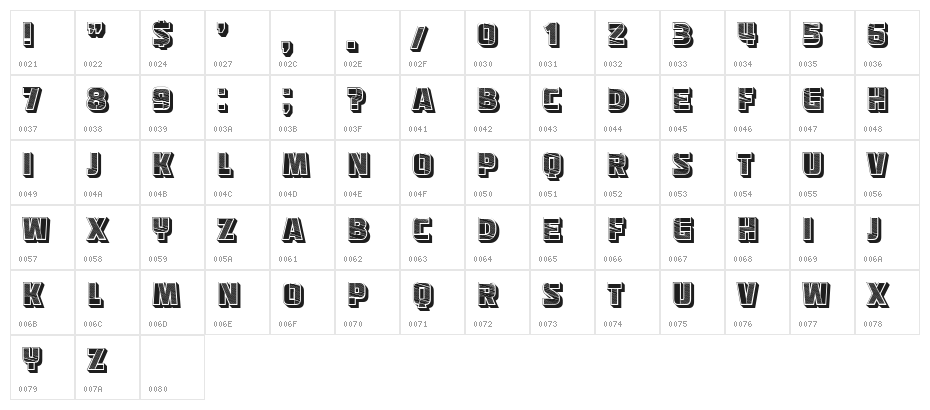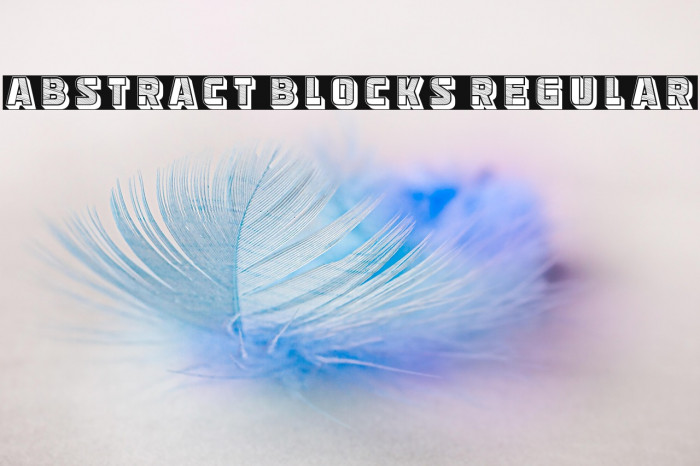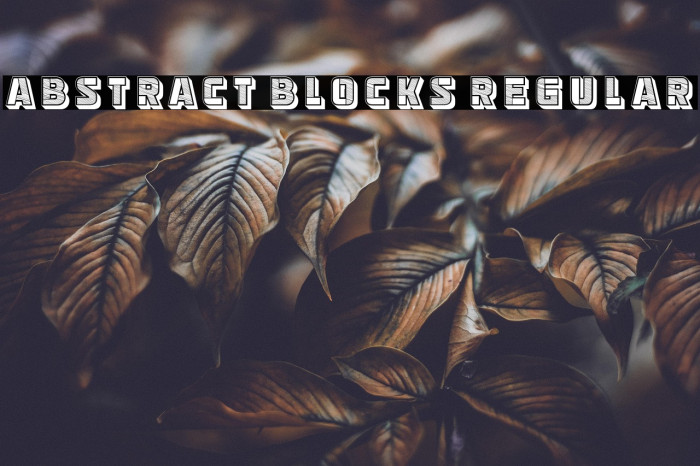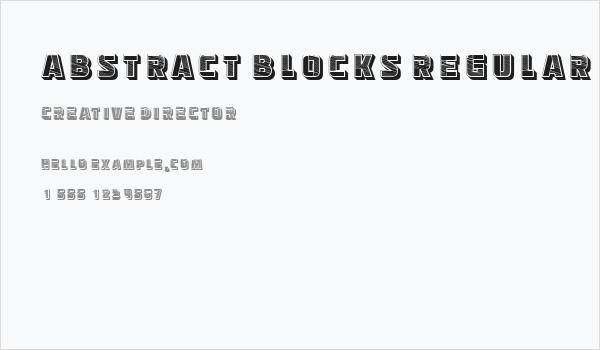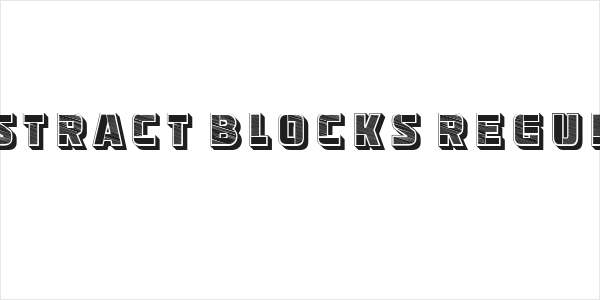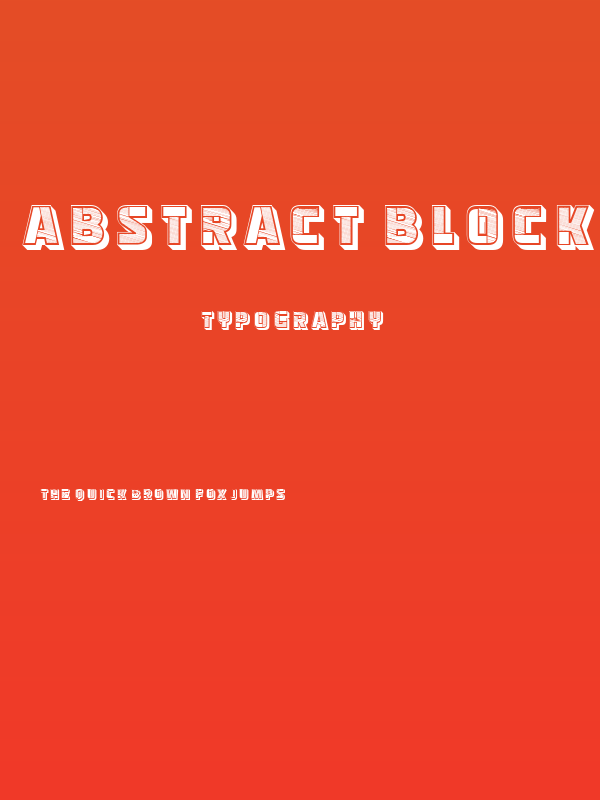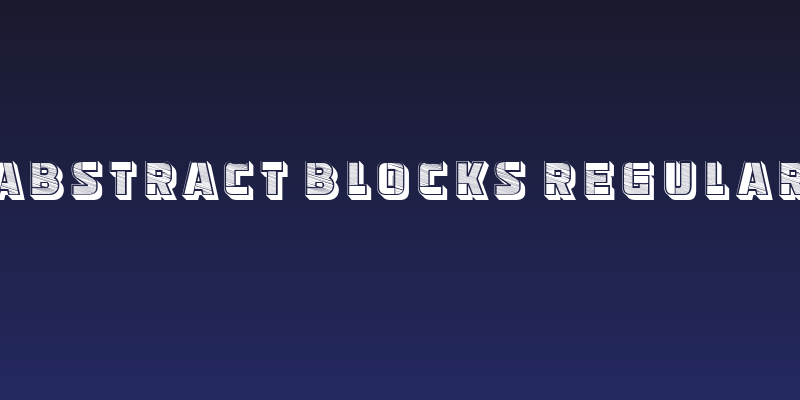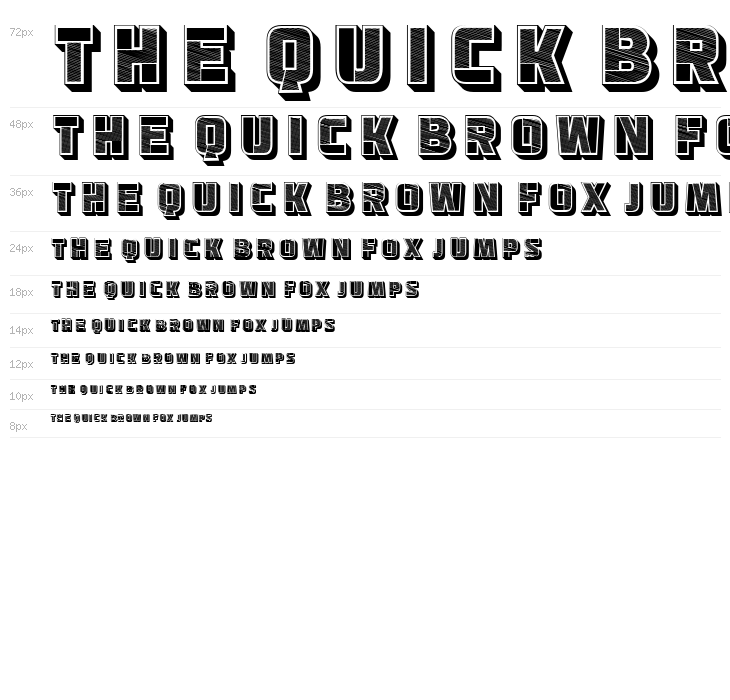
Abstract Blocks Regular Font
| Progetti proposti | Ideal for posters, logos, video game graphics, and any design project needing a bold, dynamic typeface. |